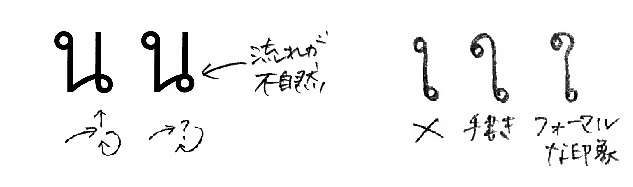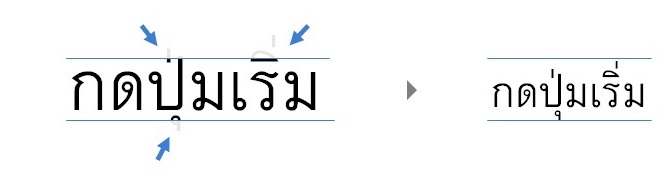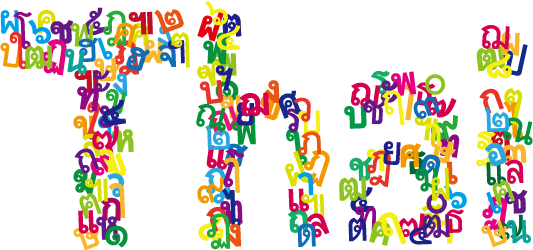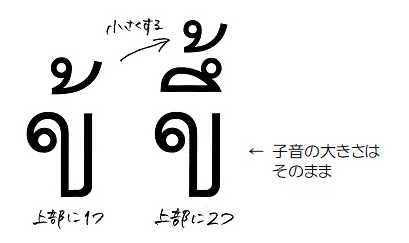
PhSansとは、Polite handwritten Sans-serif の略です。丁寧な手書きでセリフのない書体という意味をこめています。
飽きのこない書体 みなさんに長く使っていただくために。
汎用性のある書体 コンテンツに自然に溶け込むように。
違和感のない書体 現地の方に受け入れられるように。
1.できるだけシンプルに
2.できるだけ手書き風に
3.上下に見切れることがないように
機器やアプリによって上下が見切れることがありますが、当社のフォントは見切れません。
4.でもメインである子音ができるだけ大きくみえるように
上下の見切れを完全に防ぐとどうしても文字は小さくなりますが、できるだけ読みやすいデザインにしています。
長く目にするもの
例)文書の本文
何度も目にするもの
例) 組込み機器